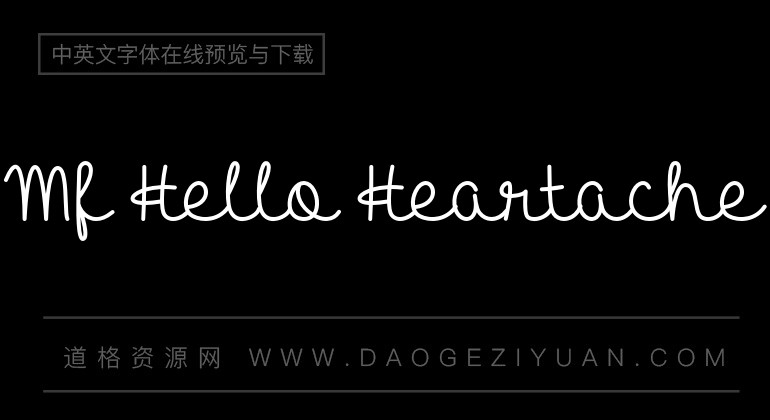
Mf Hello Heartache 是一种优美的手写风格字体,通常用于卡片设计、海报、标志、手写标签和其他设计项目。 它具有流畅的曲线和手写笔触,使得它在设计中具有非常自然的感觉。 该字体由 Misti's Fonts 设计,非常适合需要表达浪漫、柔和和温暖感觉的设计项目。它的特点是字母之间的连笔,使得整个字体看起来更加连贯和流畅。它支持大写、小写字母、数字和标点符号,使得在设计中使用时非常的方便。 Mf Hello Heartache 字体非常适用于需要表达个人、情感和独特风格的设计项目,如婚礼邀请函、手写信封、生日卡片等。内容介绍
Mf Hello Heartache是一款非常不错的手写艺术字体,具有很好的视觉感,适合于文化类的宣传设计、商业类品牌的广告和产品包装设计以及个性化文字排版等较多场景。